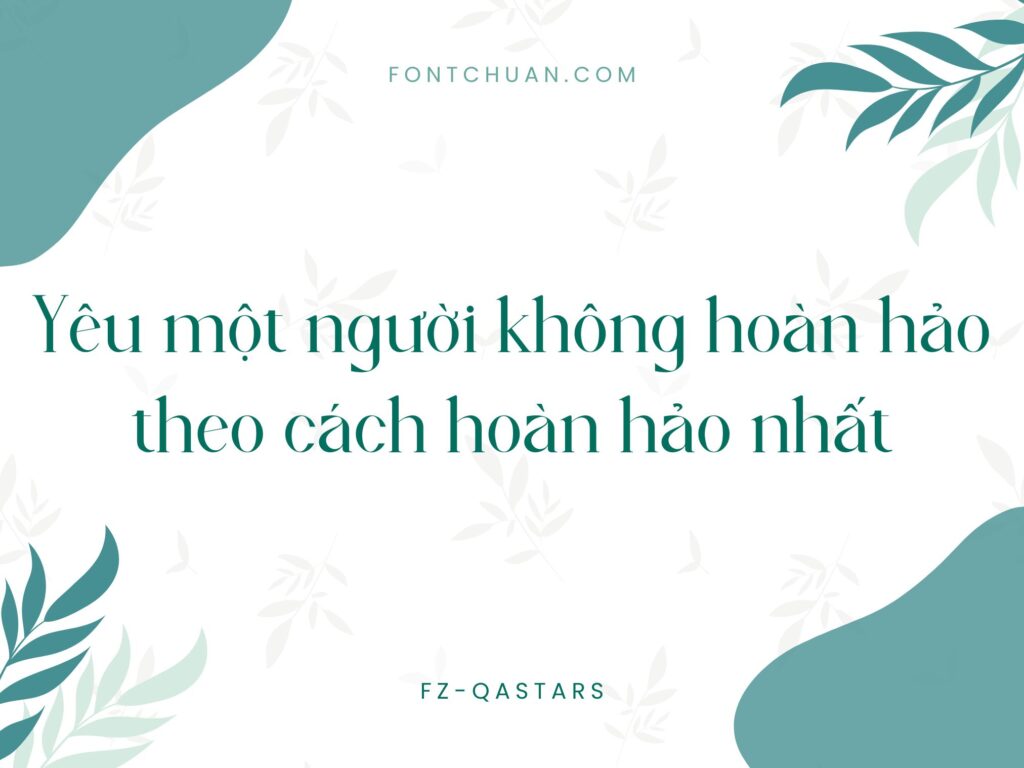
Font Fz-Qastars Việt Hóa
Fz Qastars là một phông chữ hiển thị độc đáo, được thiết kế bởi Penatic Studio. Phông chữ này mang phong cách hiện đại, với các đường nét sáng tạo, giúp tạo điểm nhấn mạnh mẽ trong thiết kế. Phiên bản Fz Qastars đã được Việt hóa bởi Fonttiengviet, hỗ trợ đầy đủ các ký tự tiếng Việt, giúp người dùng dễ dàng ứng dụng vào các thiết kế mang bản sắc địa phương.
Với kiểu dáng độc đáo và đường nét tinh tế, Fz Qastars vừa là một Font Display lý tưởng cho các tiêu đề, banner và ấn phẩm cần sự nổi bật, vừa có thể được sử dụng như một Font chữ thiệp cưới hiện đại, mang đến vẻ đẹp phá cách nhưng vẫn tinh tế cho các thiết kế thiệp mời, thiệp chúc và các sản phẩm in ấn đặc biệt. Font này phù hợp cho các ứng dụng như thiết kế logo, tiêu đề, banner và các sản phẩm sáng tạo khác. Về ngành nghề, Fz Qastars đặc biệt phù hợp với lĩnh vực quảng cáo, công nghệ, giáo dục và các ngành nghề sáng tạo trong thiết kế.